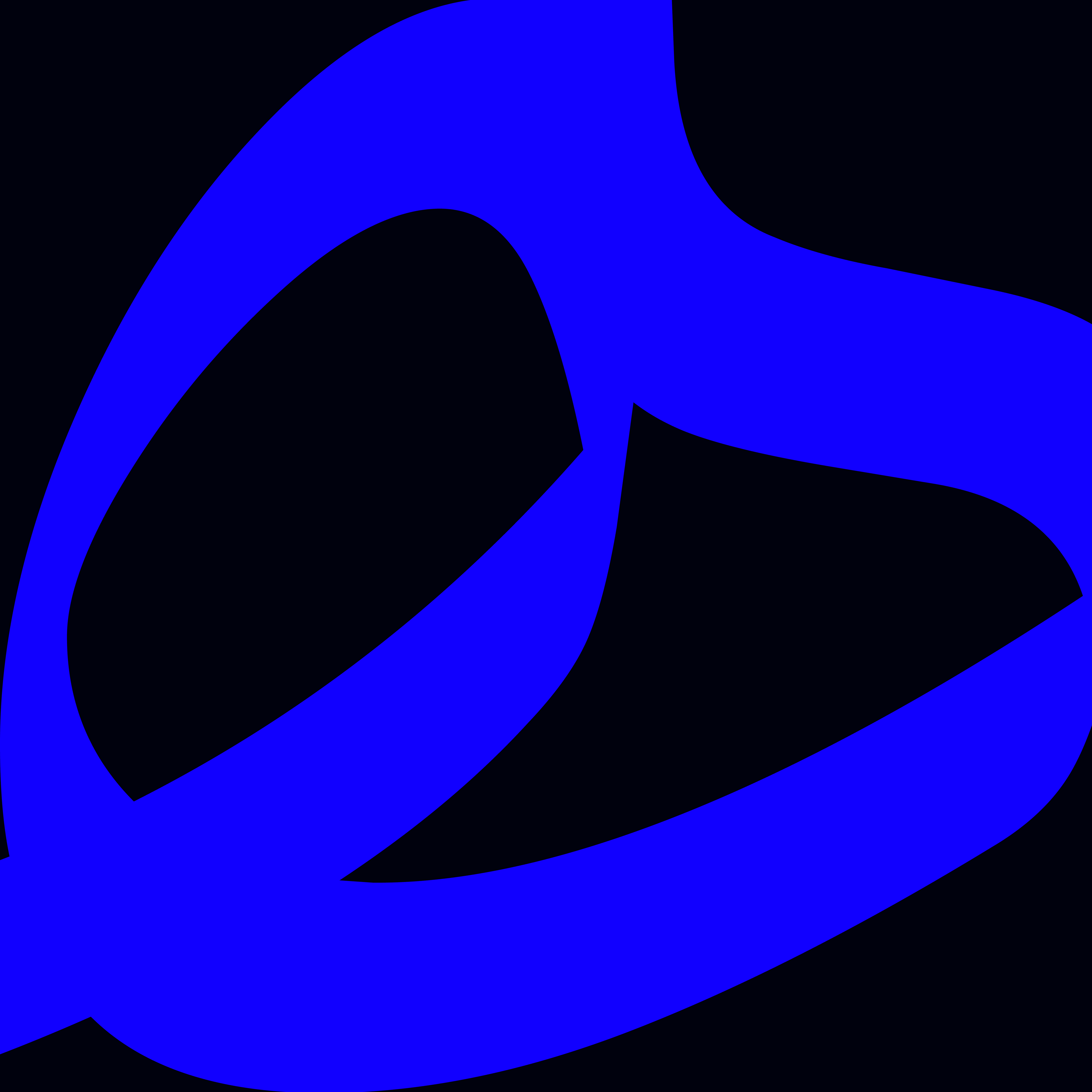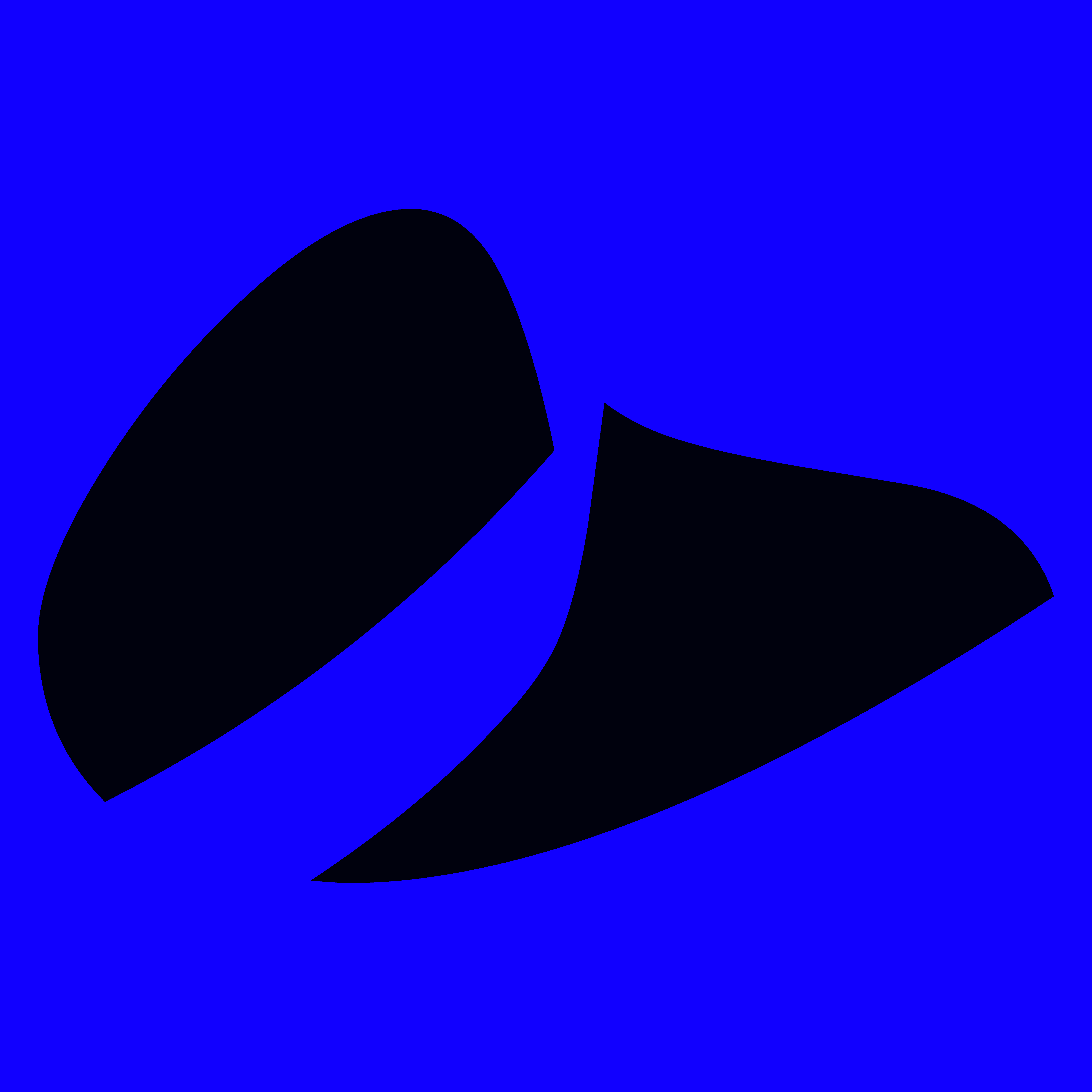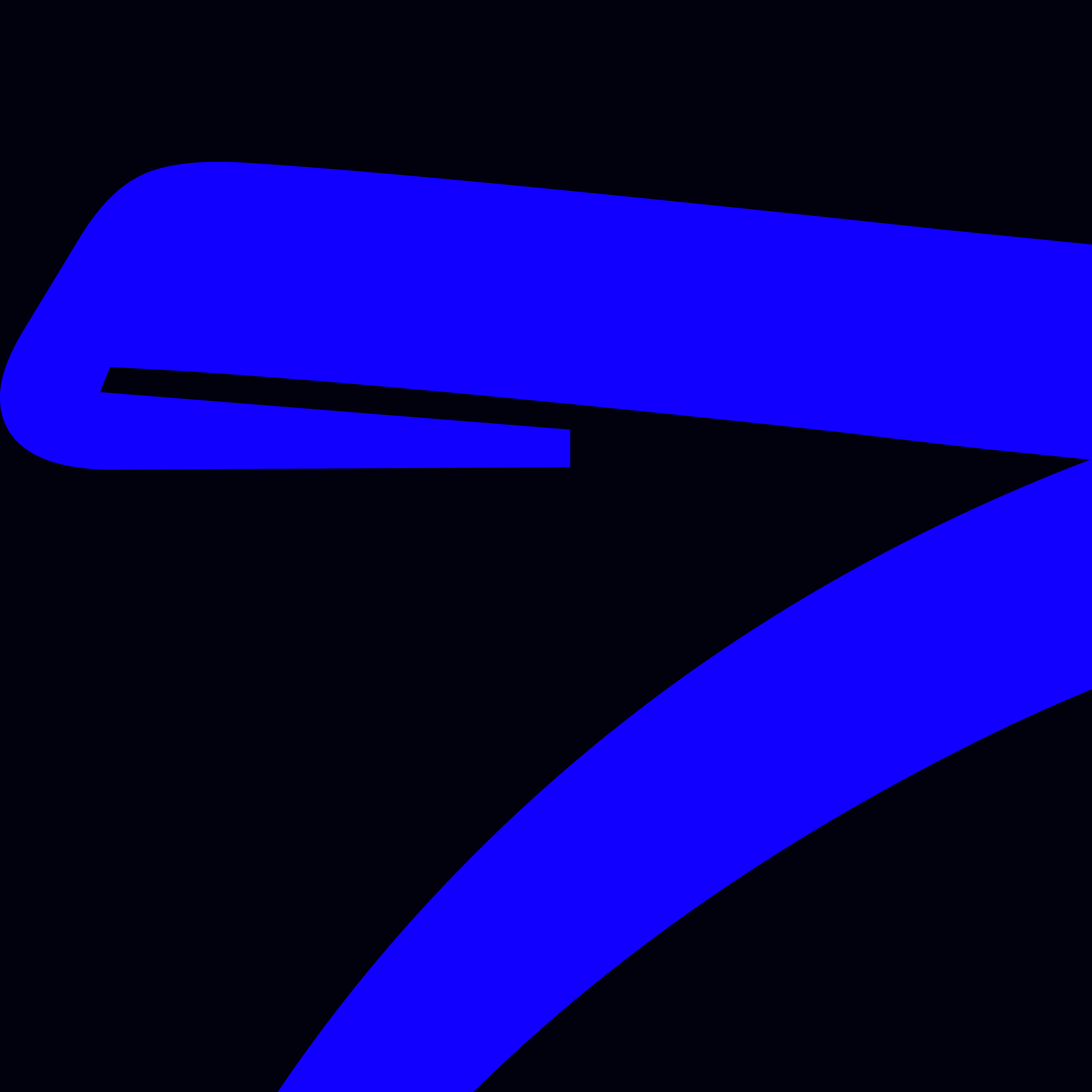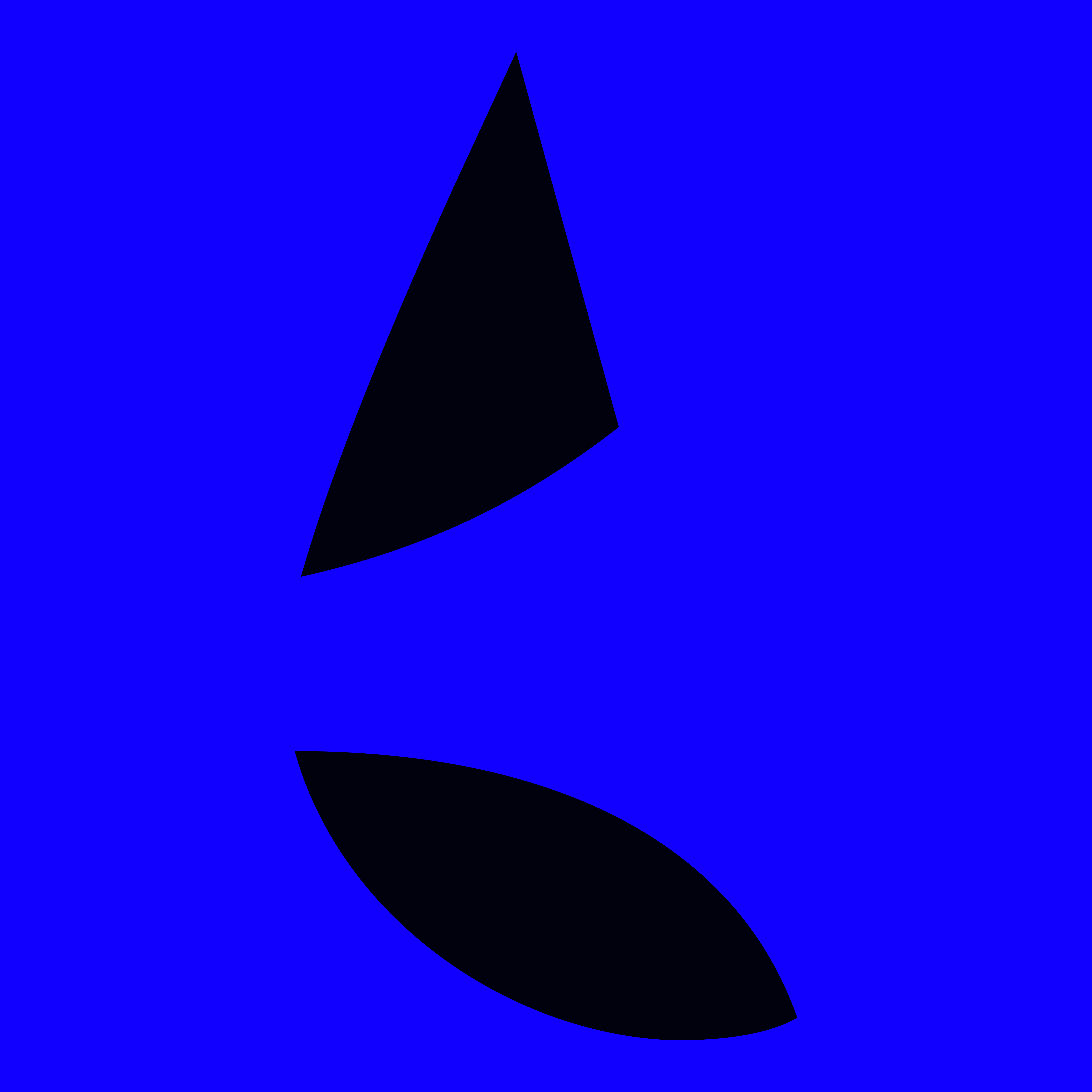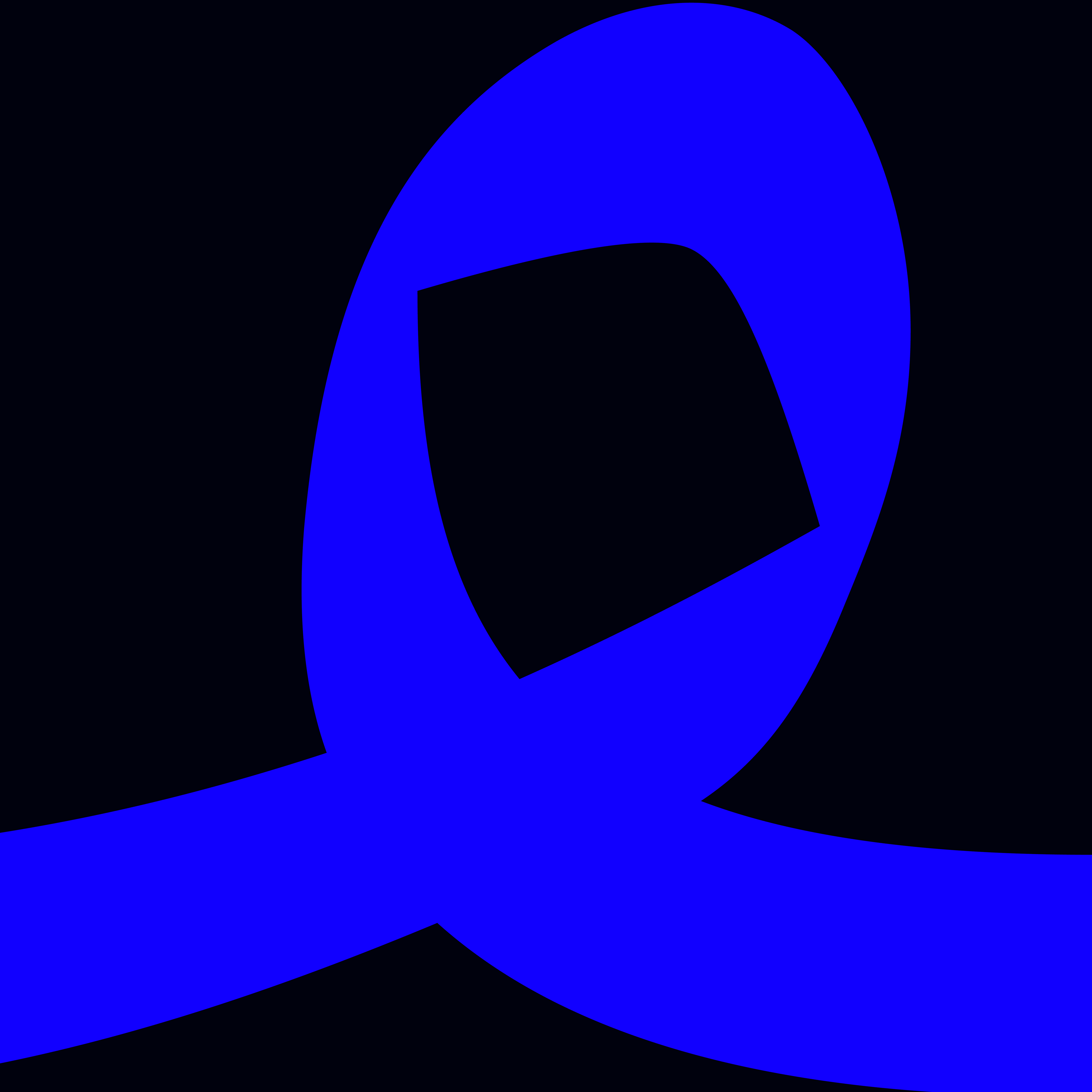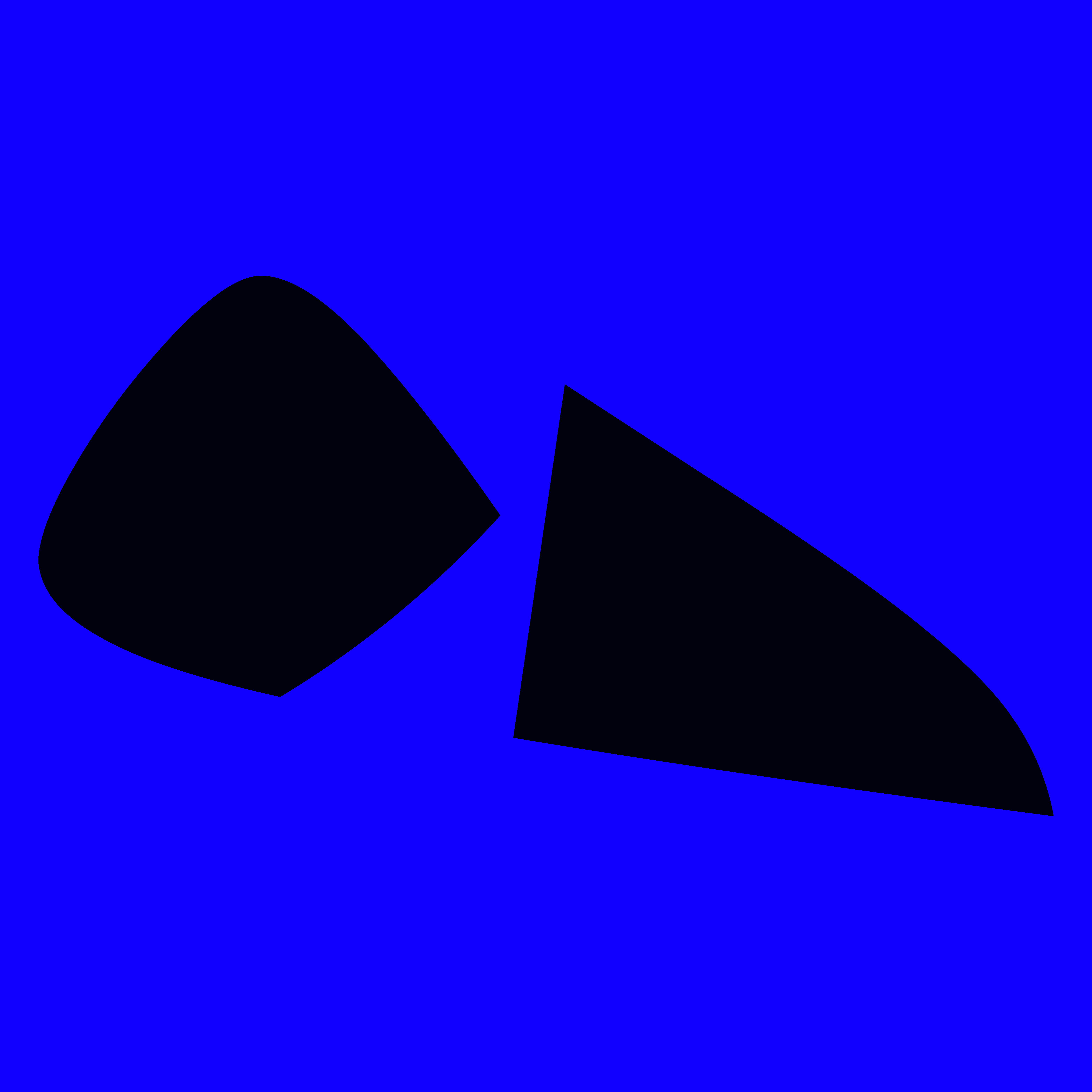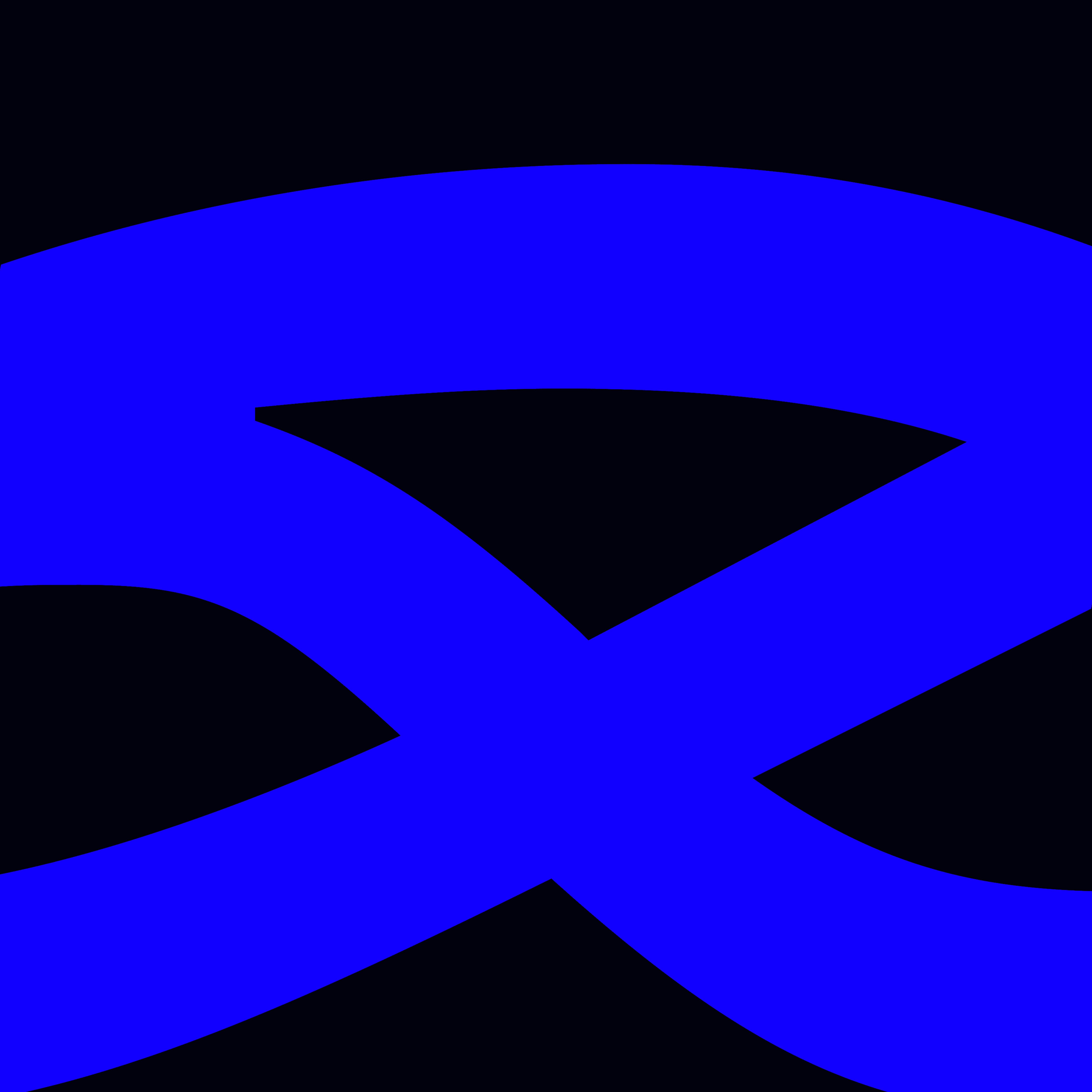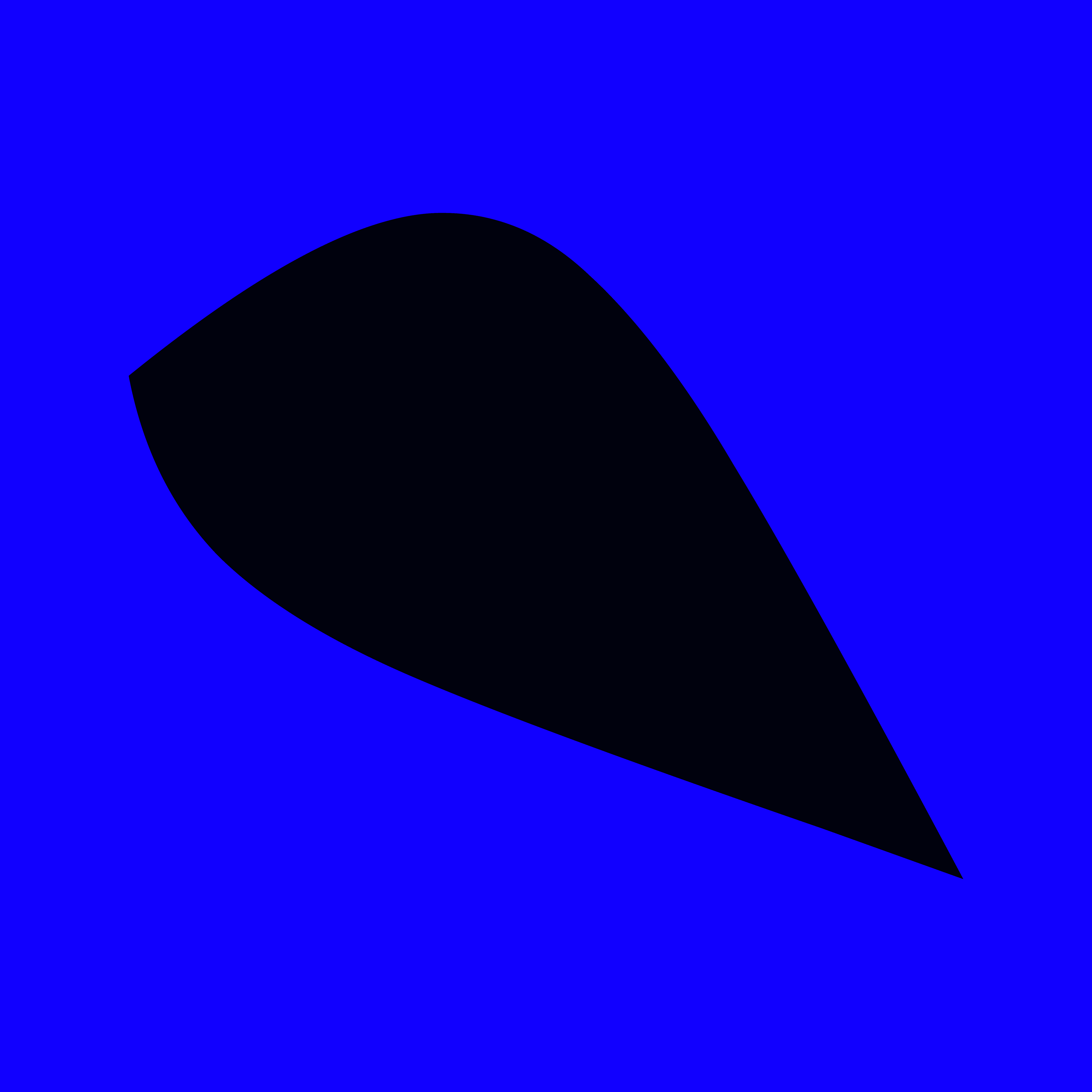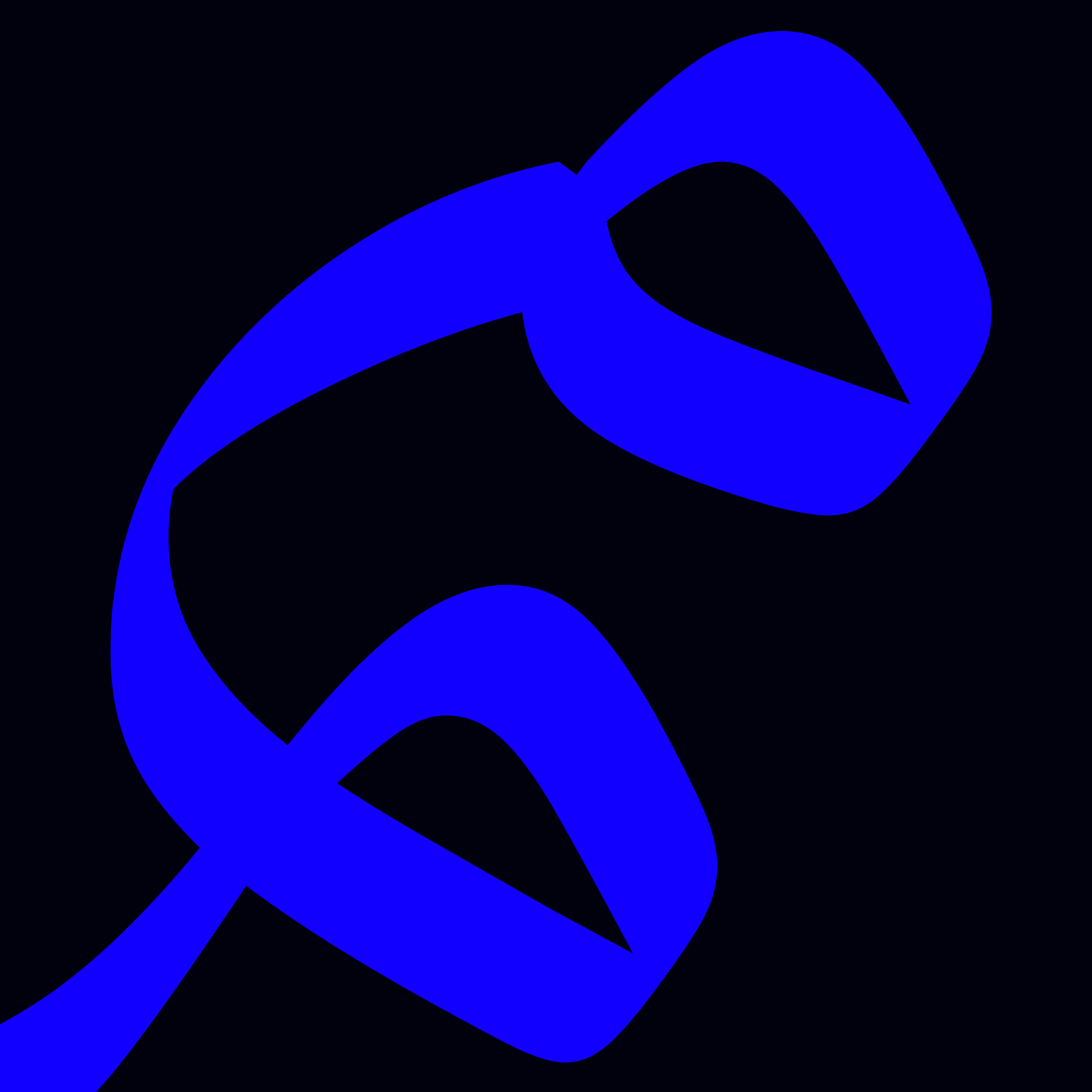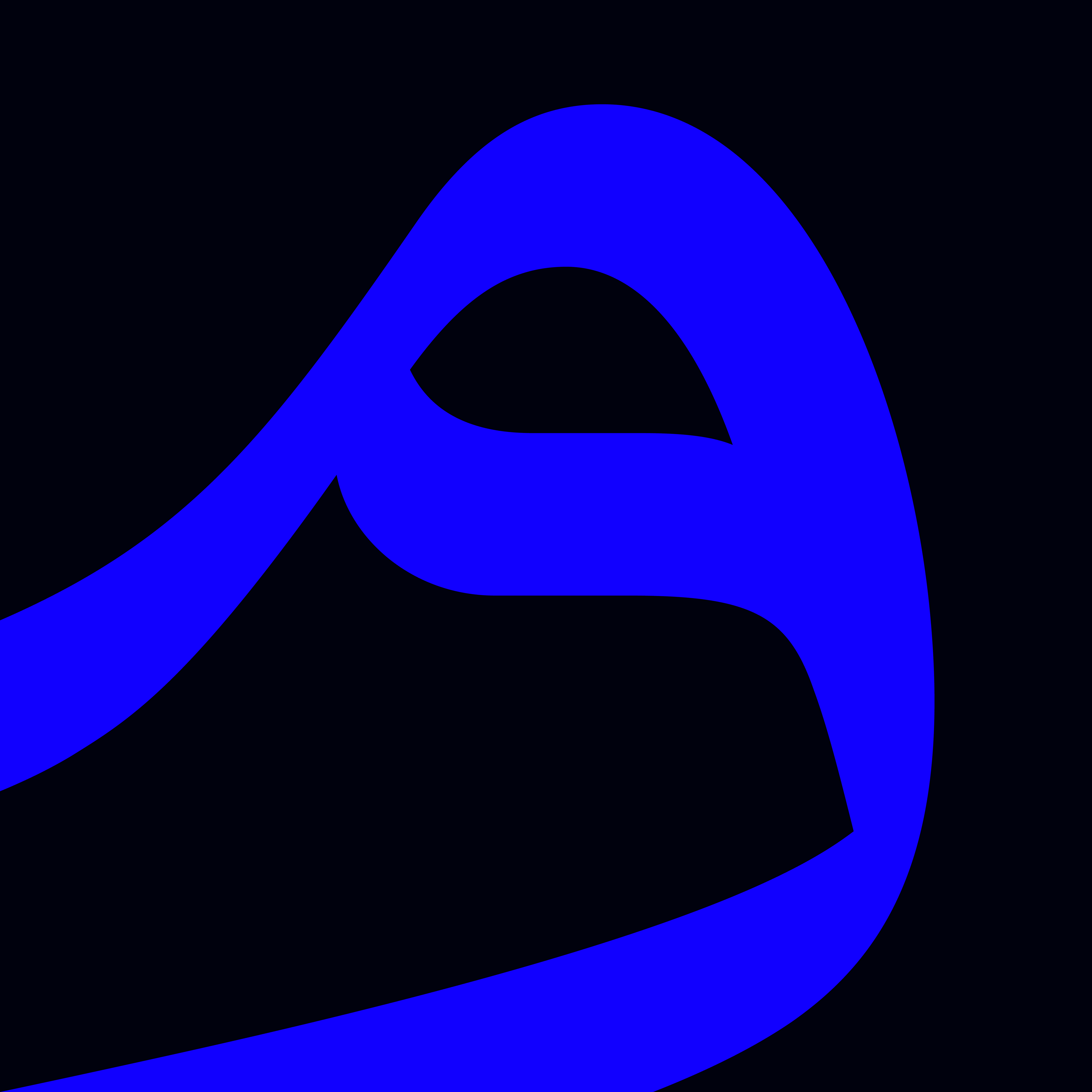
دانگ دارای روحیه حماسی و تاریخی است، انگار که گویی از دل تاریخ برآمده است، قد و قامت کشیدهی حروف بر روحیهی حماسی این تایپ فیس می افزاید. دانگ مناسب استفاده در فضاهای مختلف گرافیکی است.
از ویژگیهای بصری بارز این تایپفیس میتوان به برتری سطح به دور، داشتن طره در برخی از حروف نظیر الف/ ب/ ج/ د و ط اشاره کرد.انتهای حروف و ر م به صورت آزادانه نوشته و ارسال میشدند. به دلیل کشیدگی عمودی برخی حروف، کلمات حول محور خط کرسی تجمع پیدا میکنند و موجب ایجاد سبکی و سنگینی در متن میشوند و گاهاً سواد و بیاض جالبی ایجاد میکنند. به دلیل طول کشیده ارسالهای "و" "ر" "م" گاهاً این حروف باهم ریتم ایجاد میکنند یا برای حروف برای کلمات بعدی فضا خالی میکنند تا حروف بعدی را در دل خود جای دهند.
دانگ دارای لیگچرها و حروف جایگزین زیادی میباشد که دست طراحان و تایپوگرافرها را برای ایجاد اثری جذاب باز میگذارد. این لیگچرها و حروف جایگزین باعث ایجاد تنوع میشوند و کمک میکنند تا متن برای مخاطب مورد نظر، خواندنیتر بشود.
این تایپفیس به غیر از زبان فارسی از زبان عربی/اردو/کوردی و انگلیسی پشتیبانی میکند.
در تایپفیس لاتین سعی شده تا حروف با همنشینی در کنار فارسی یا عربی خاکستری یکسانی نمایش بدهد و از لحاظ طراحی با یکدیگر تفاهم داشته باشند و از لحاظ کنتراستی برابر باشند. تایپ فیس لاتین نیز دارای لیگچرهایی است میتواند برای متن و عنوان کاربرد داشته باشد.